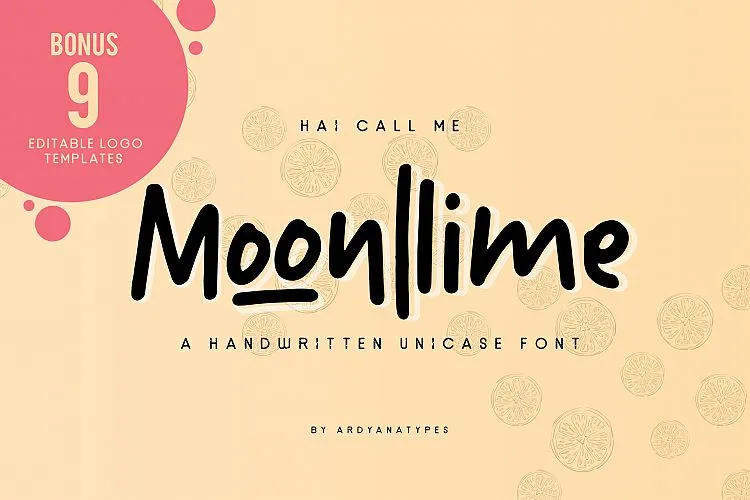
Descubra a Moonllime Script Font, uma fonte script perfeita para sua próxima criação ou projeto criativo. Criada pelo designer Ardyanatypes, a Moonllime Script é uma elegante fonte de tipo casual e simples que combina interessantes traços à mão. Através do uso das três variações disponíveis — solid, chalk e outliner — você terá inúmeras opções para personalizar seus projetos. Além disso, a Moonllime Script oferece muitas características abertas únicas, como ligações, estilos alternativos, swashes e muito mais. Este recurso de tipo é especialmente adequado para criar logomarcas, citações, designs de roupas, convites de casamento ou qualquer outra forma de arte que você possa imaginar. Com sua beleza única e seu apelativo design, a Moonllime Script pode ajudar a destacar seu trabalho ao torná-lo ainda mais único e distintivo. Descubra como essa fonte pode revolucionar suas próximas criações!